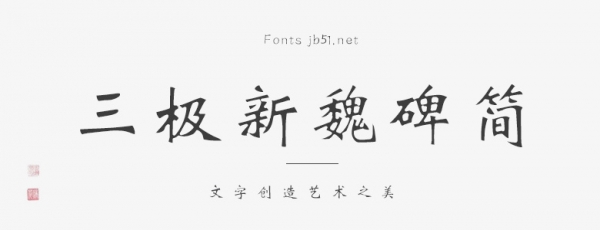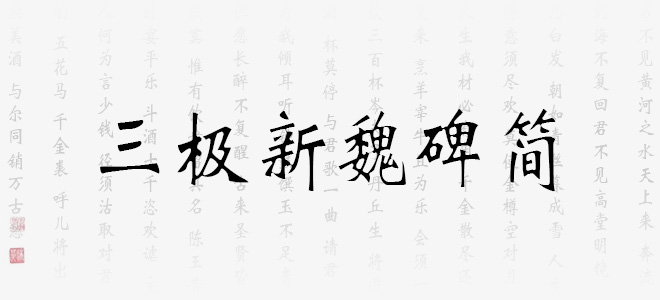
三極新魏碑簡是以魏碑字型為本,筆畫細(xì)致流暢,結(jié)構(gòu)緊湊,筆意拙中帶巧,不避鋒芒。充分體現(xiàn)了漢晉隸書與唐楷之變化,字形筆意盡顯。適用于各類便攜式屏幕的系統(tǒng)嵌入字體,以及傳統(tǒng)印刷媒介的標(biāo)題與正文排版。在品牌形象設(shè)計中作為logo設(shè)計性文字視覺效果更佳。
三極新魏碑簡